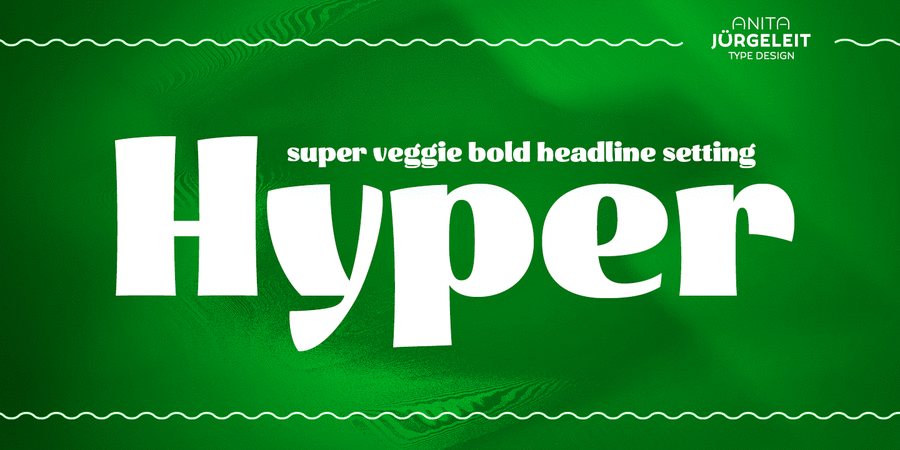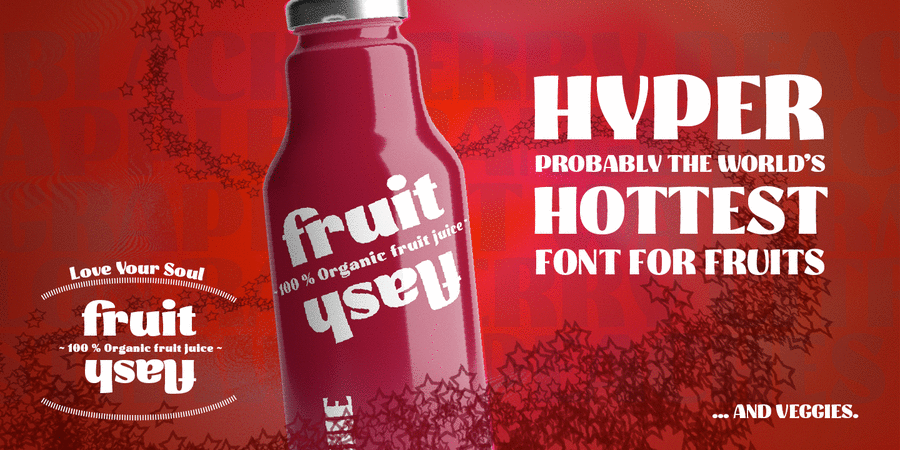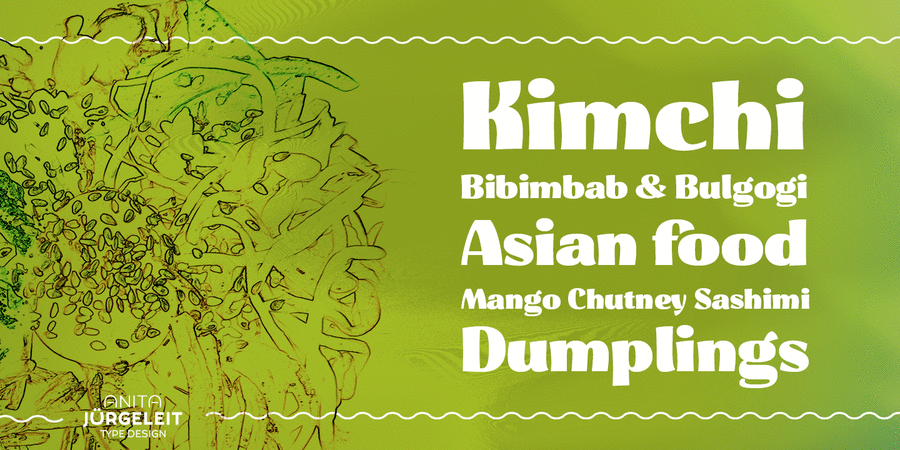
Hyper – це максимально заголовковий шрифт для фруктів, овочів, квітів та усіх красивих і здорових речей, які наповнюють ваше життя радістю і задоволенням. Hyper найкраще виглядає на великих і навіть величезних розмірах. Тому, для тонкої настройки дизайну, Hyper відображається у двох основних накресленнях: Hyper Black створений для заголовків, логотипів. Hyper Grande зроблений для дуже великих написів на плакатах або великих банерах. Воно має трохи більше елегантності за рахунок тонших горизонтальних штрихів. Добре сформовані літери Hyper римуються одна з одною та ніби тримаються за руки.
Особлива увага приділяється літері f, яка адаптує свою форму, щоб укласти наступну літеру в затишне обійми. Для цього зроблено 62 спеціальні F-лігатури, які управляються open-type фачами.
Hyper підтримує всі необхідні функції: мінускульні цифри, під і надрядкові індекси, дроби, чисельники та знаменники, багато лігатур.
Шрифт розробила Аніта Юрґелайт у 2019 році.
щедрий, смачний, переконливий, добрий, радісний, позитивний, важкий, яскравий, помітний, добродушний, душевний, стійкий, довірчий, сильний, пузатий, товстий, старомодний, оригінальний, потішний, сімейний, активний, домашній, щасливий, тісний, веселий, задерикуватий, смішний, доброзичливий, грайливий, привітний, свіжий, стиглий, соковитий, дитячий, наївний, милий, мультяшний, літній, пишний, приємний, живий, гладенький, святковий, усміхнений, апетитний, зелений, природний, натуральний, рясний, насичений, пухкий, різкий, чіткий